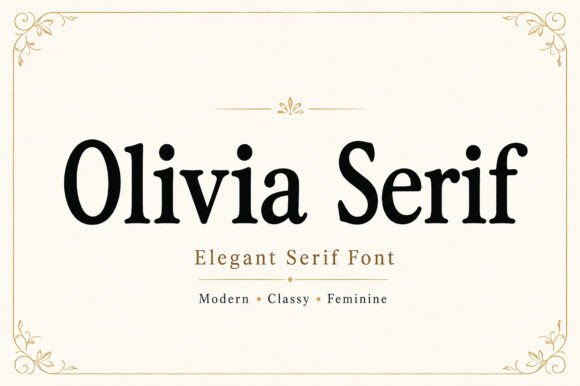
Olivia Serif
Jika anda sedang mencari aset berkualiti tinggi seperti Olivia Serif, pakej premium ini merupakan pilihan yang hebat untuk projek kreatif anda.
Dicipta dengan ketepatan, Olivia Serif menyediakan vektor yang bersih, tipografi yang licin dan lesen komersial untuk ketenangan fikiran.
Sama ada anda mencipta produk POD (Print on Demand), jemputan perkahwinan atau grafik media sosial, Olivia Serif amat bersesuaian.